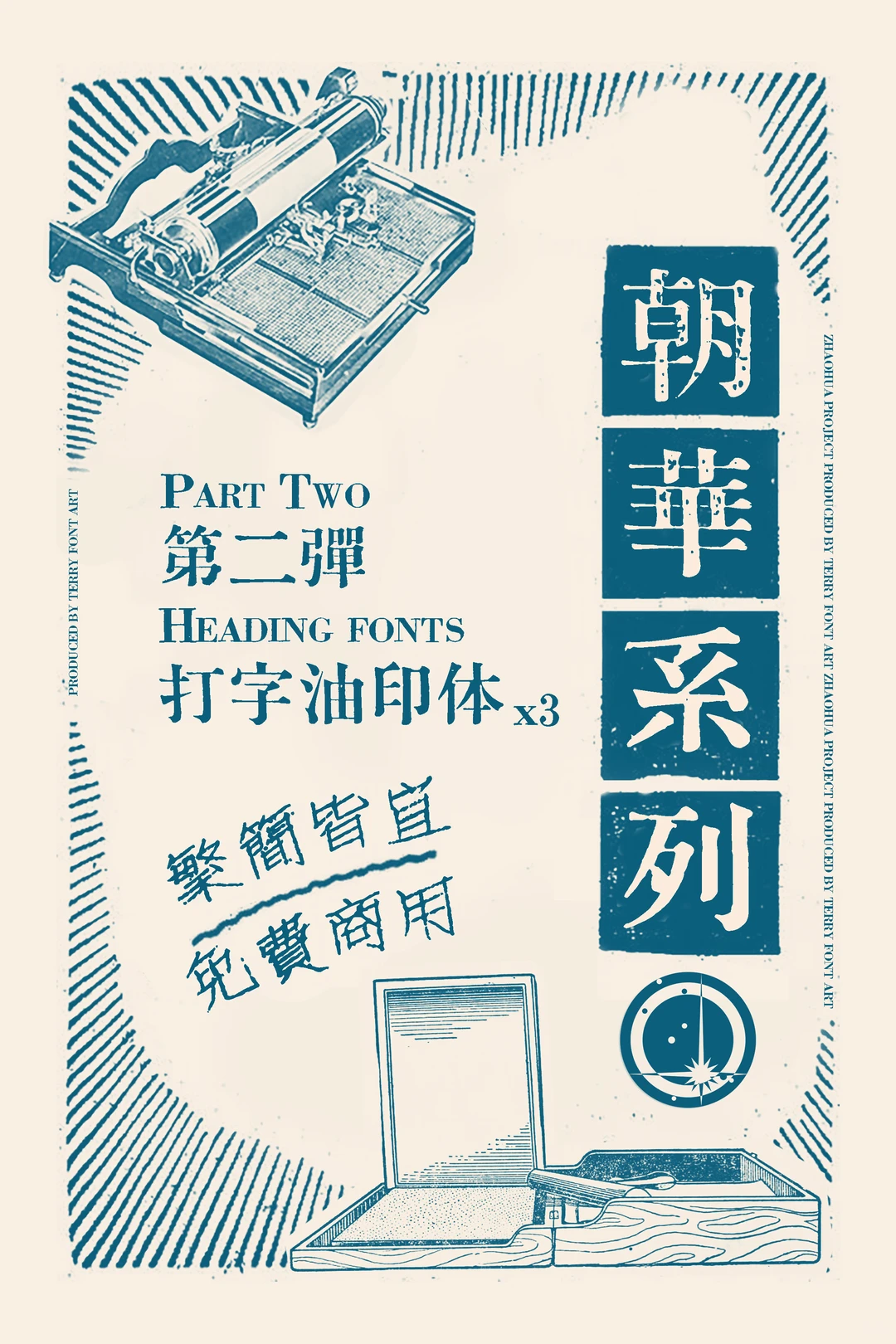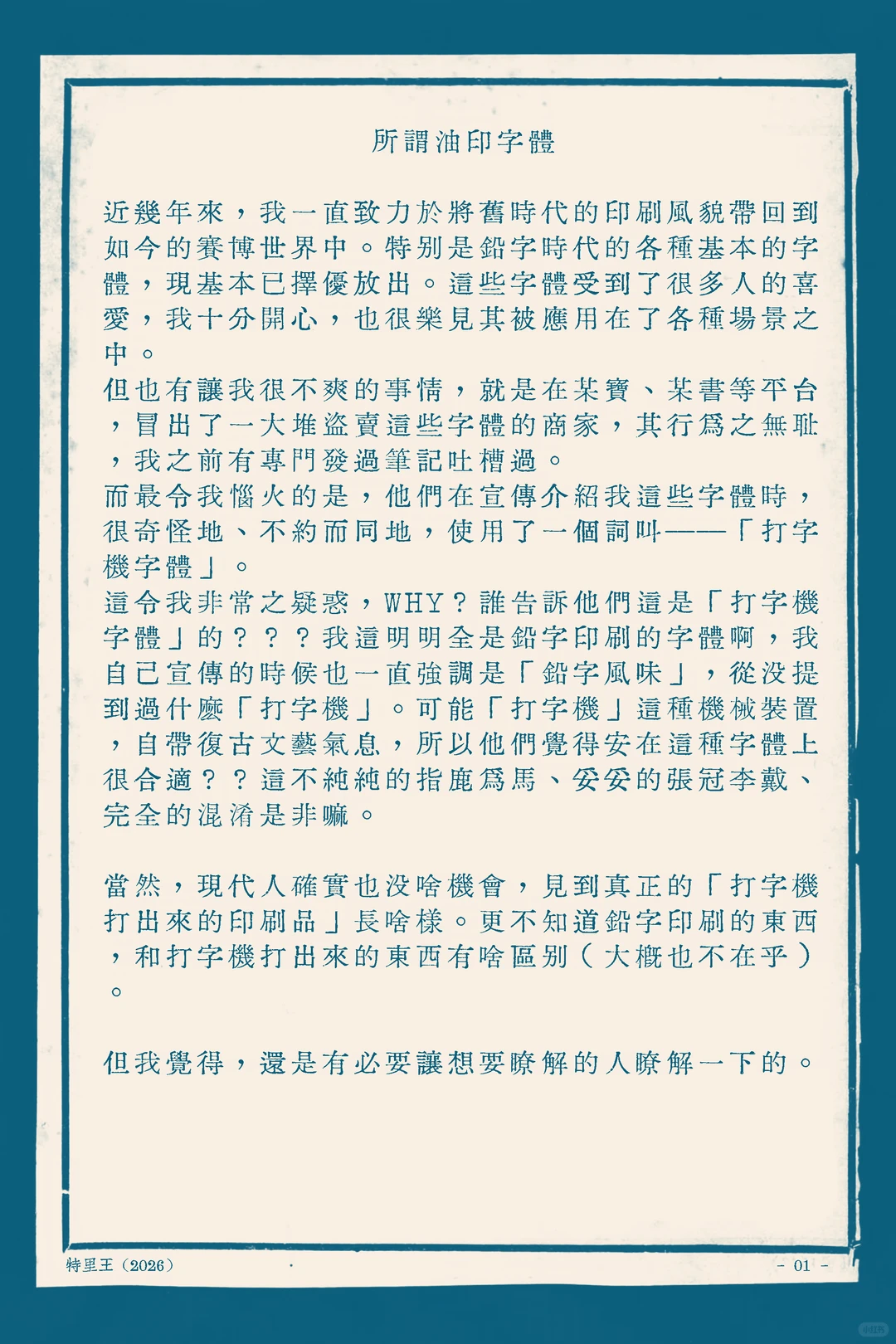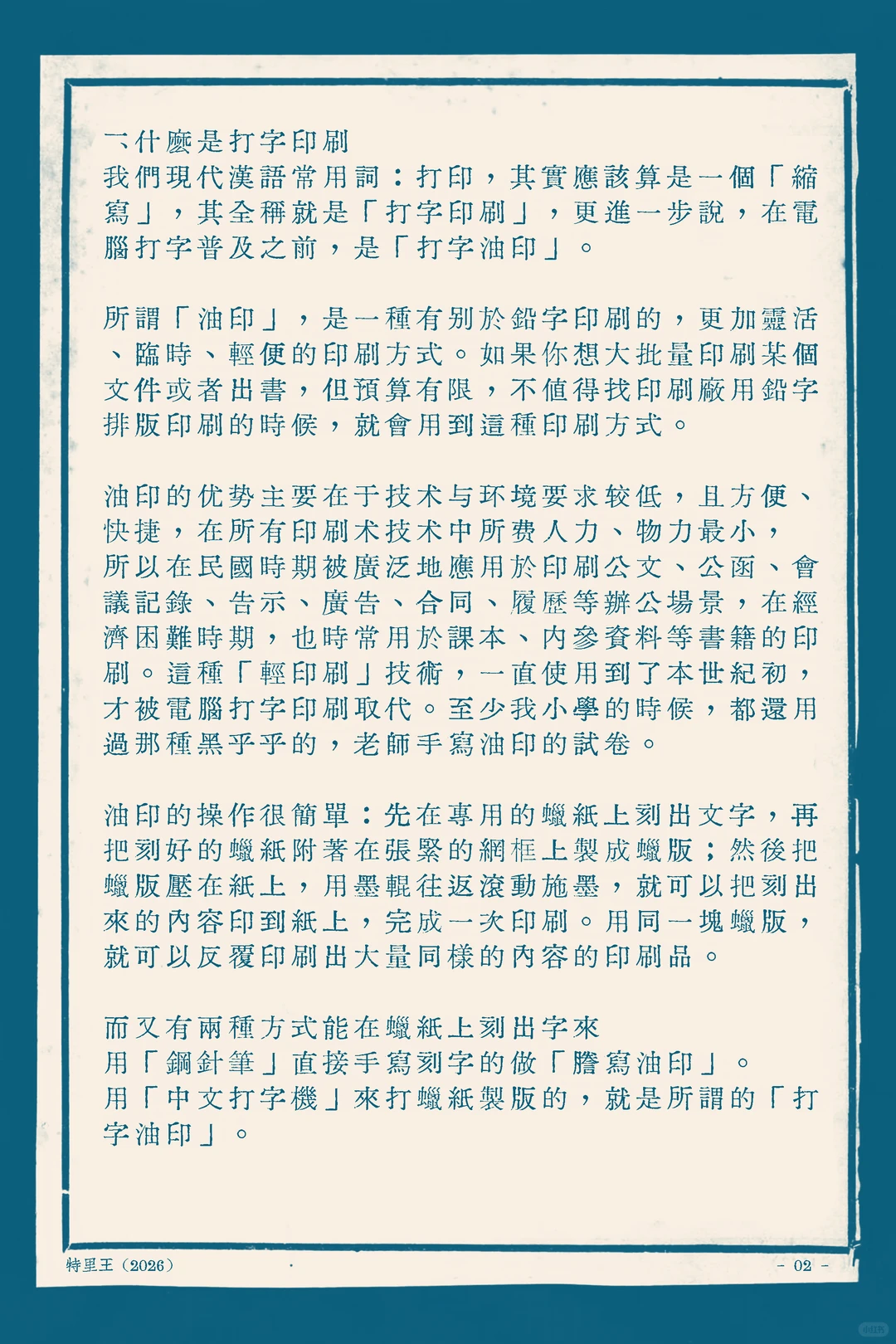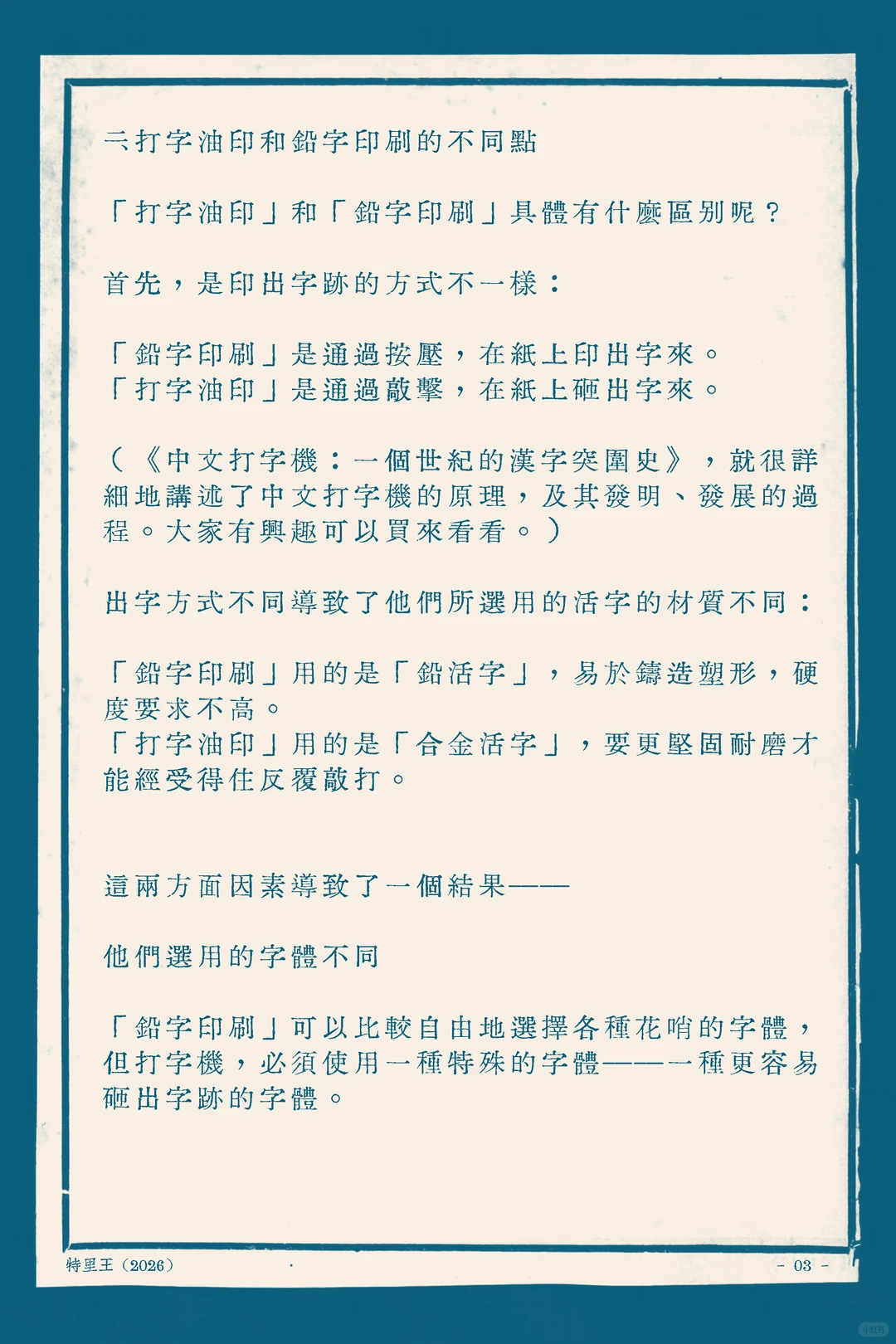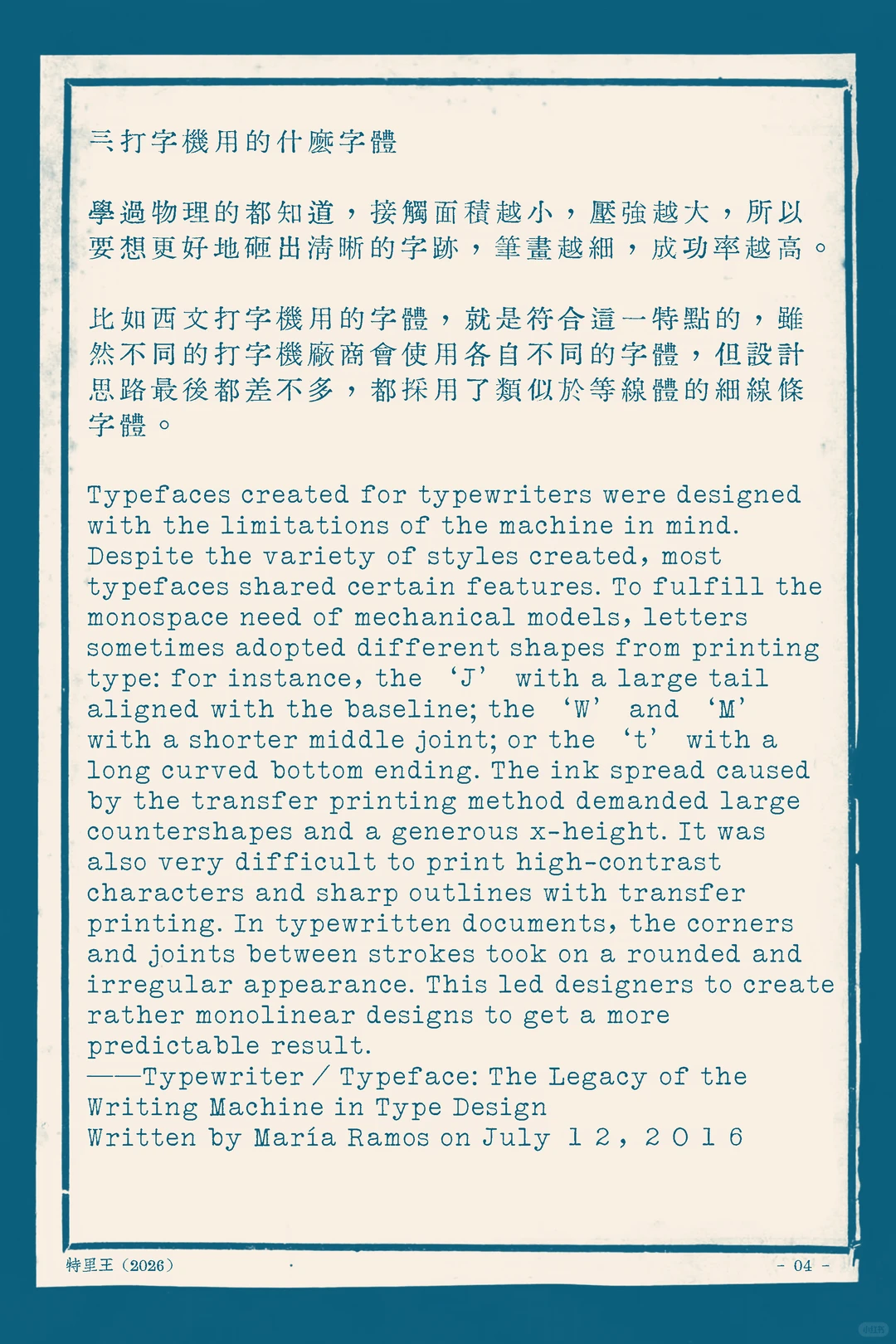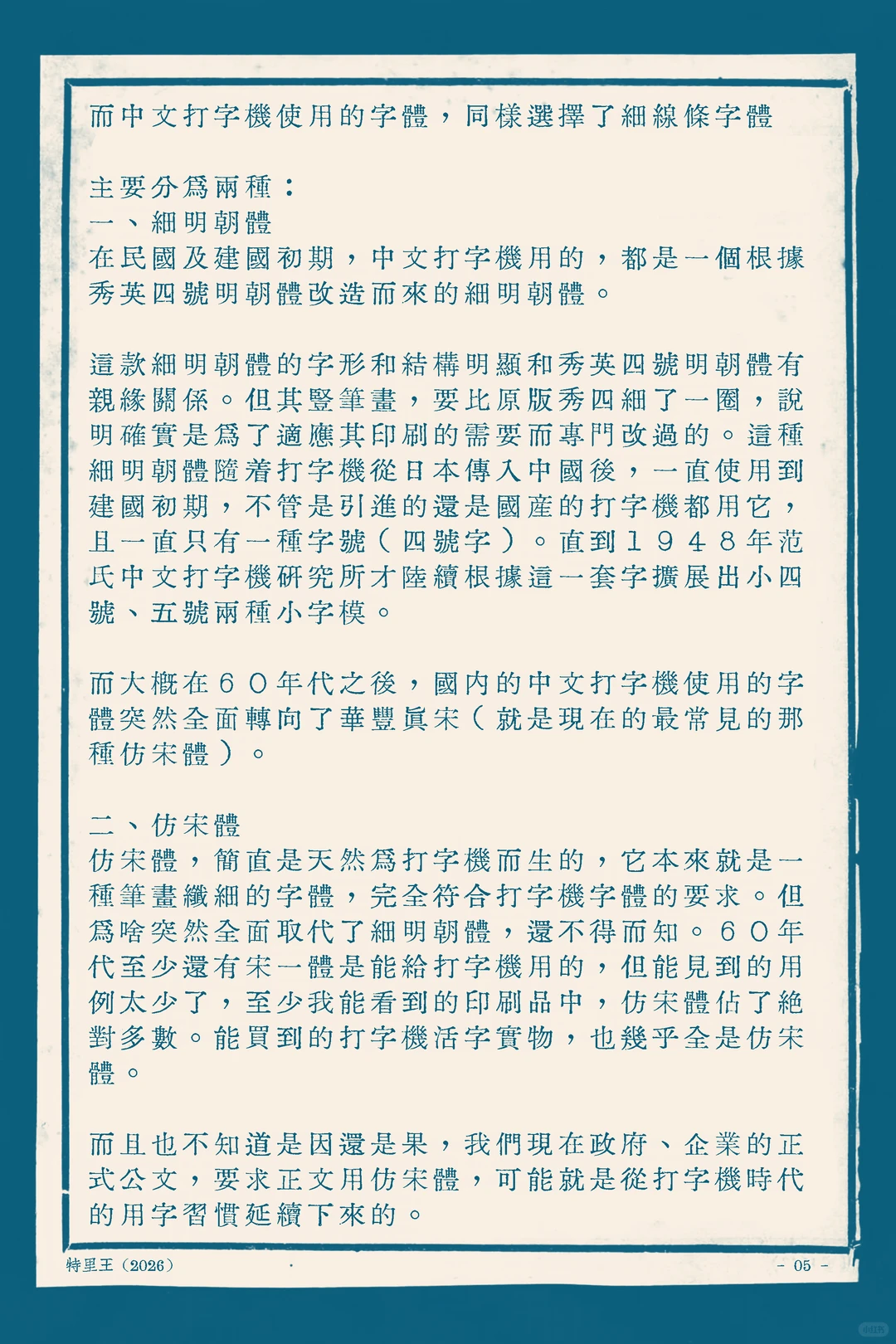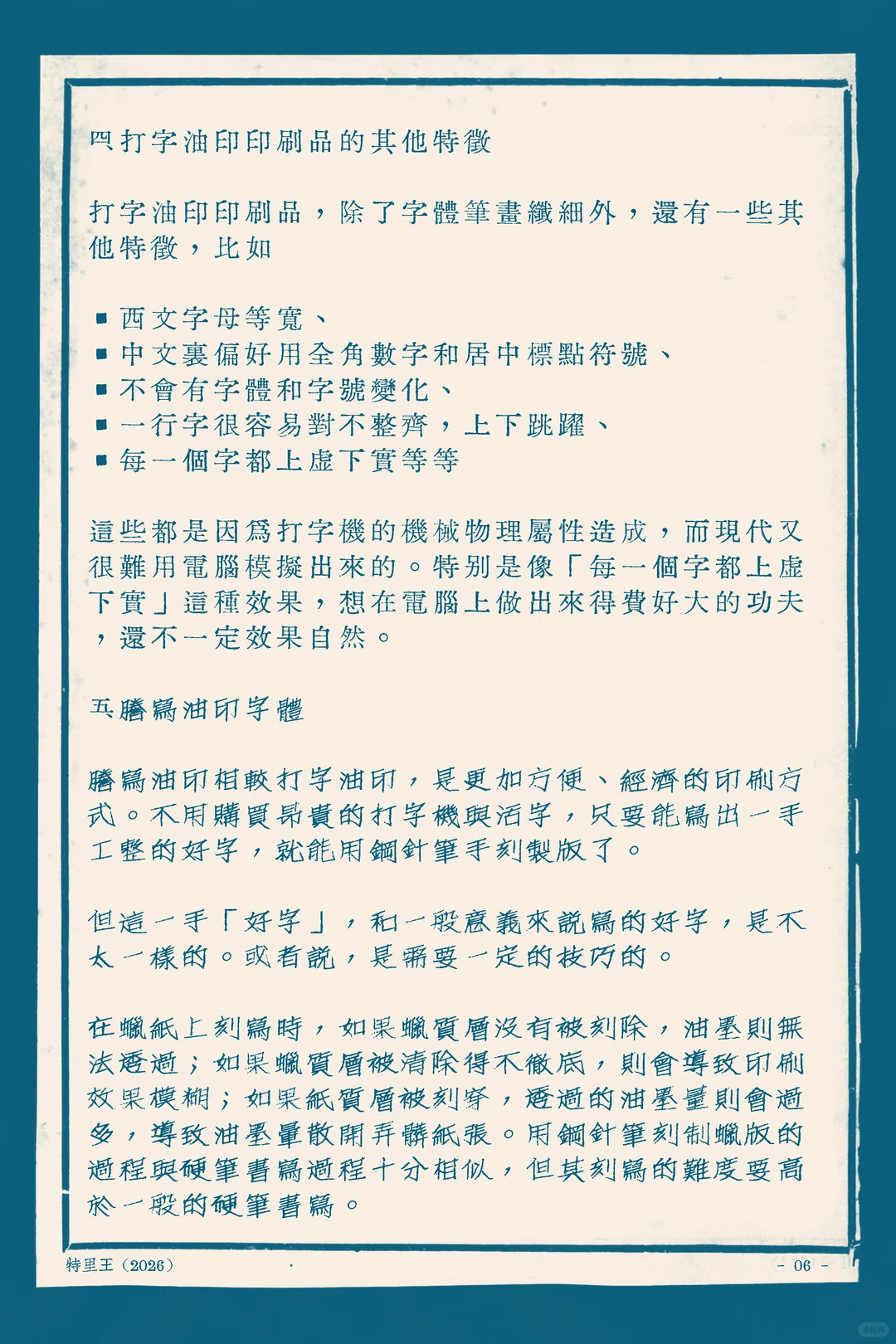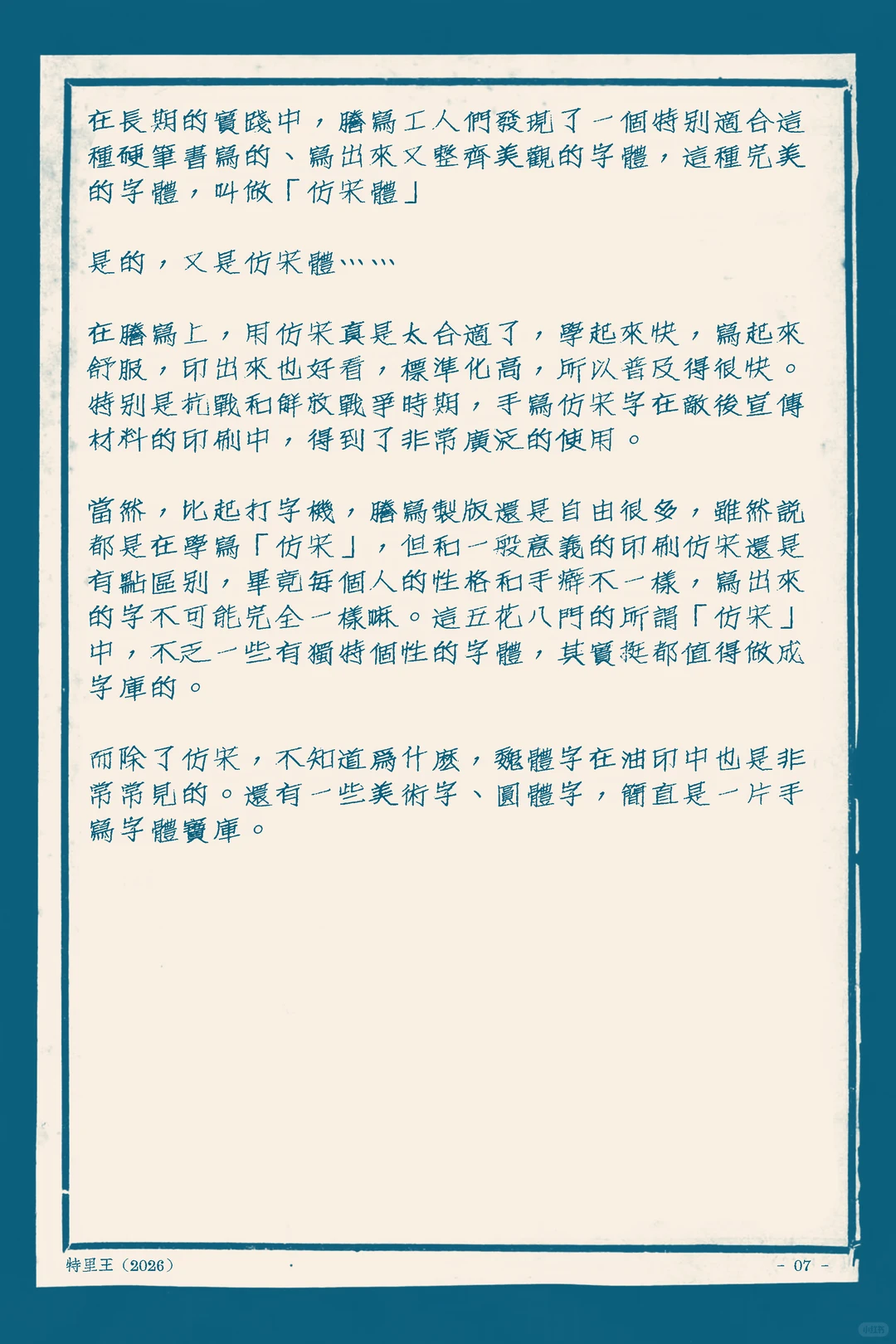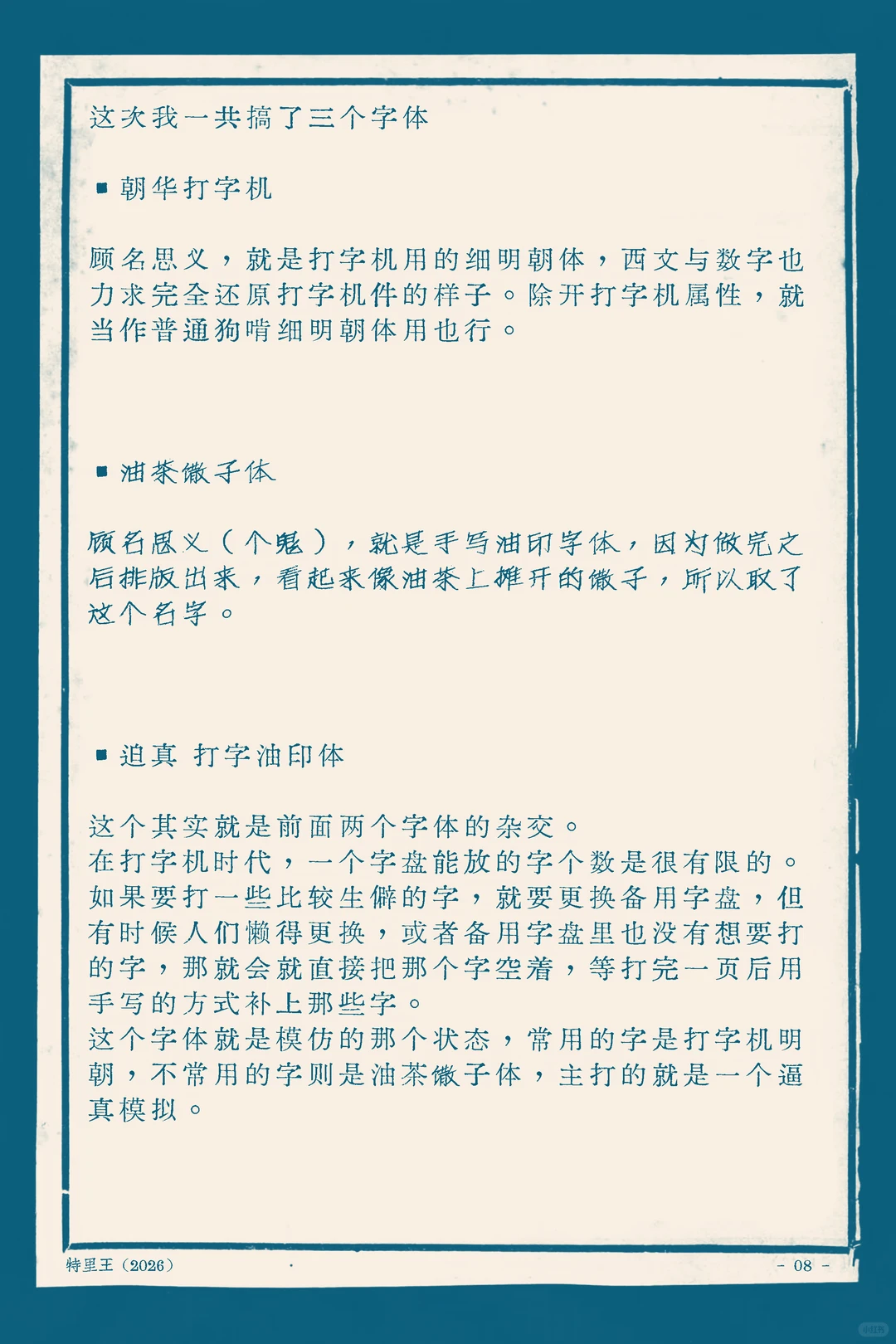
迫真打字油印体这个其实就是前面两个字体的杂交。在打字机时代,一个字盘能放的字个数是很有限的。如果要打一些比较生僻的字,就要更换备用字盘,但有时候人们懒得更换,或者备用字盘里也没有想要打的字,那就会就直接把那个字空着,等打完一页后用手写的方式补上那些字。这个字体就是模仿的那个状态,常用的字是朝华打字机,不常用的字则是油茶馓子体,主打的就是一个逼真模拟。
朝华系列第二弹标题字体打字油印体宣传图,繁简皆宜且免费商用,含复古打字机与墨盒插图。-刊刻Kntuk
所谓油印字体:这几年我致力于推广铅字字体,却苦恼于某宝某书有人盗卖,还误叫它打字机字体。我强调的明明是铅字风味,他们却指鹿为马。现代人虽难见真迹,但我觉得有必要让大家了解清楚。-刊刻Kntuk
这篇内容讲了打字印刷和油印。油印是灵活轻便的印刷法,以前预算不够印大批量文件就用它,操作是在蜡纸上刻字套网框滚墨印刷,分钢笔手写和打字机制版两种。-刊刻Kntuk
这页文本对比了打字油印和铅字印刷的差异,指出两者在印字方式(按压与敲击)、活字材质(铅活字与合金活字)及字体选择上均不相同。作者特里王。-刊刻Kntuk
打字机字体受机械限制与墨迹扩散影响,多采用等线体细线条、大x-height及圆角设计,以确保打印清晰可预测。-刊刻Kntuk
中文打字机字体主要用细明朝体和仿宋体,60年代后仿宋体取代细明朝体,现在的公文用字习惯可能就是这么延续下来的-刊刻Kntuk
本文介绍打字油印印刷品的其他特征,如西文等宽、上下跳跃,以及蜡纸油印字体的刻制技巧与难点-刊刻Kntuk
这页手写笔记介绍了“仿宋体”在硬笔书写和油印中的优势与历史应用,还提到了手写仿宋的个性特点及其他手写字体,底部署名特里王。-刊刻Kntuk
这次我一共搞了三个字体。朝华打字机是还原打字机件的细明朝体;油茶子体是排版像油茶上馓子的手写油印体;迫真打字油印体是前两者杂交,主打逼真模拟打字机缺字手写补全,常用字用明朝体,不常用用馓子体。-刊刻Kntuk
真实打字油印件样貌,展示多份旧式文档,含上海第一医学院公共卫生学院1954年实习简报、打字油印正文、手写签名及日程表。-刊刻Kntuk